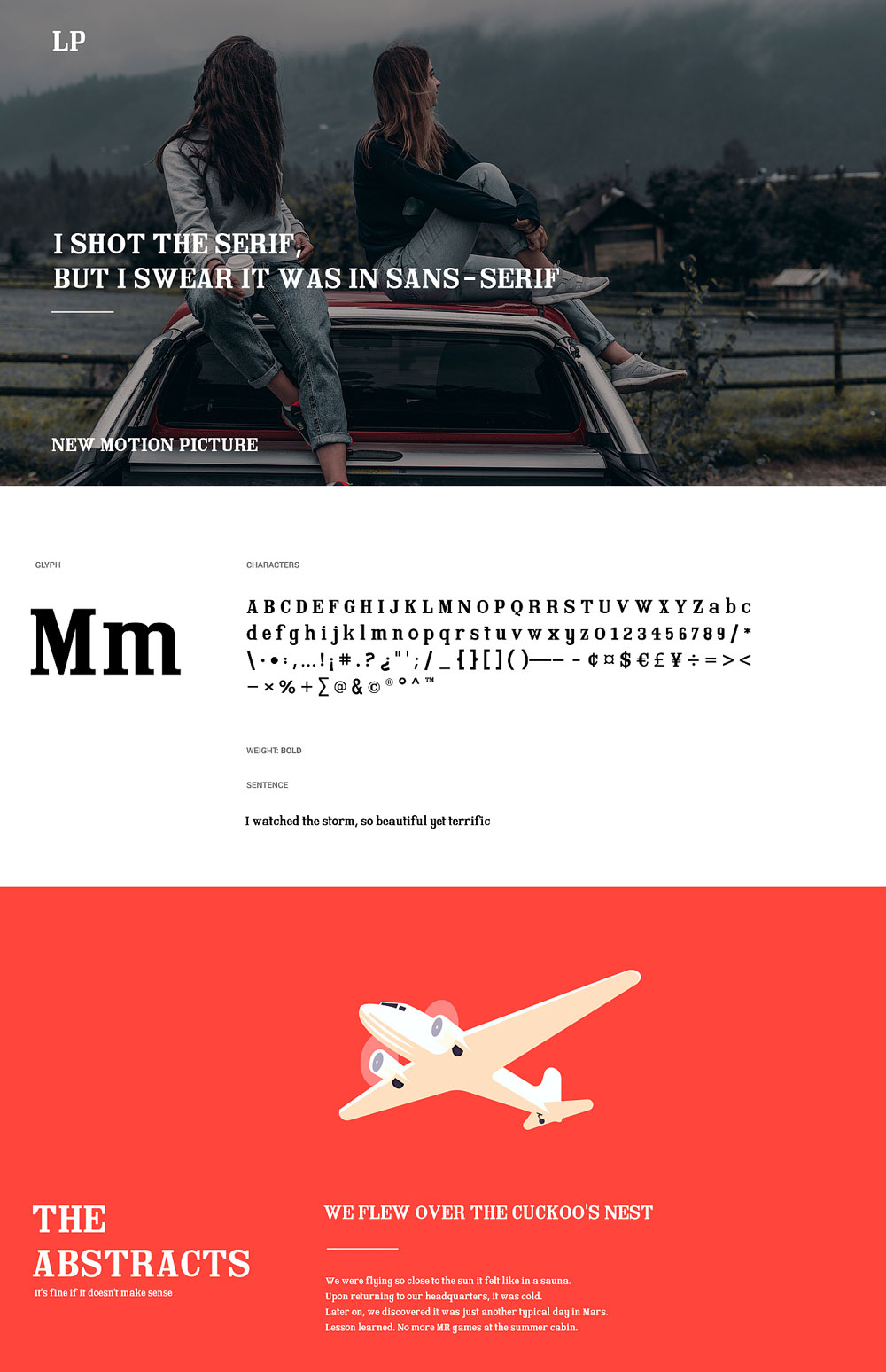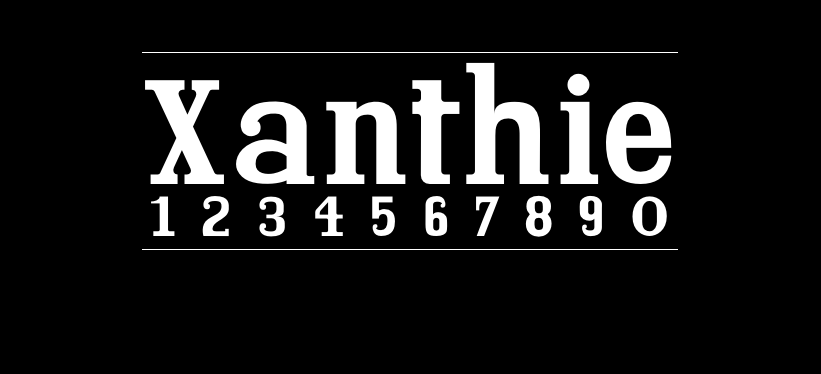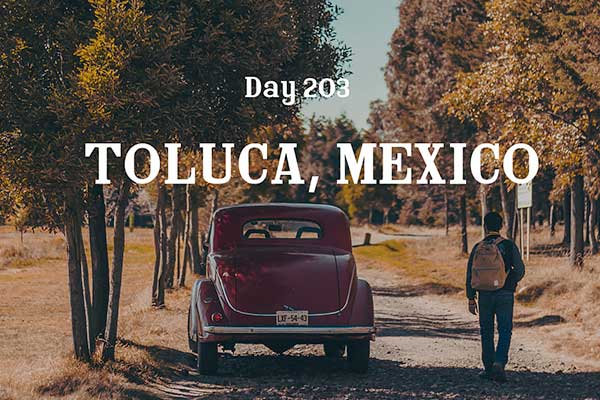
Xanthie是设计师simoherold创作的一款免费字体,一种带有怀旧感的serif字体。Xanthie的灵感来源于一本经典儿童的法语字母学习书。Xanthie特别适合需要大标题的设计。Xanthie字体首发于站酷,介绍信息中虽然没有写关于商用的信息,但是其文件下载中附上了license,这里给大家贴出来